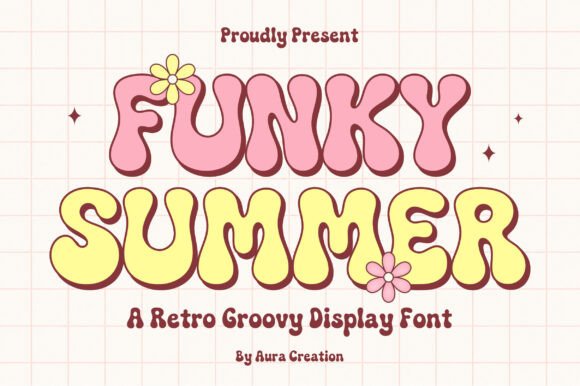
Funky Summer
Funky Summer – A Fonte Retro que Transforma Seu Projeto de Verão
Se você está à procura da tipografia perfeita para capturar a energia vibrante de dias ensolarados, festas na praia e até mesmo a Christmas in July, Funky Summer é a escolha ideal. Esta fonte display traz um visual groovy e playful, inspirado nos anos 70, que garante destaque imediato em qualquer peça criativa.
- Estilo retro e hippie: Letras arredondadas e cheias de personalidade que lembram a era psicodélica dos anos 70.
- Design bold e bubbly: Traços grossos e suaves que facilitam a leitura mesmo em tamanhos grandes.
- Versatilidade de uso: Perfeita para t‑shirts, pôsteres, tote bags, adesivos, branding e designs de verão.
- Vibração de verão: Cores e formas que evocam sol, mar, areia e a diversão de uma festa ao ar livre.
Por que escolher a Funky Summer?
Além da estética irresistível, Funky Summer oferece:
- Impacto visual imediato – Ideal para chamar a atenção em vitrines, capas de redes sociais e campanhas publicitárias.
- Facilidade de aplicação – As formas arredondadas permitem combinações fáceis com outras fontes sem perder a harmonia.
- Sentimento nostálgico – Conecta seu público a memórias de verão, viagens à praia e festas descontraídas.
- Alta legibilidade mesmo em cores contrastantes, garantindo que sua mensagem seja lida de primeira.
Aplicações Ideais
- Camisas e camisetas personalizadas para eventos de verão.
- Pôsteres de festivais, festas na piscina e promoções de férias.
- Tote bags e sacolas ecológicas com estampas divertidas.
- Adesivos e stickers para laptops, garrafas e pranchas de surf.
- Identidade visual de marcas que desejam transmitir um clima alegre e descontraído.
Com Funky Summer, seu projeto ganha o toque groovy e sunny que só uma fonte retro pode oferecer. Seja para branding, merchandising ou arte gráfica, esta tipografia garante que sua mensagem brilhe como o sol de julho. Não perca tempo – adicione Funky Summer ao seu arsenal criativo e eleve suas criações de verão a outro nível!